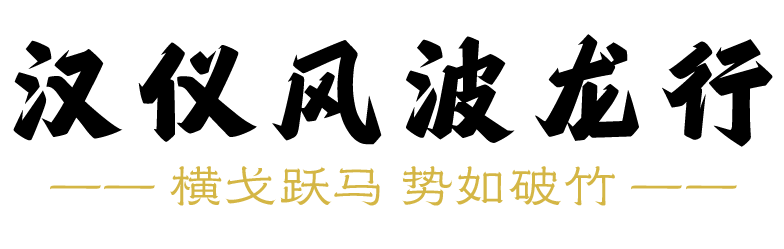
汉仪风波龙行字体介绍,看字体如何行走江湖,势如破竹!
粗壮 / 阳刚 / 动感 / 潇洒
标志 / 书籍 / 广告 / 杂志 / 游戏 / 动漫 / 影视 / 包装
汉仪风波龙行是一款将粗黑体与行楷字体有机结合的字体,由汉仪签约设计师梁风波创作。这款字体既保留了黑体粗壮有力的特征,由能展现出行楷字体的流畅自如的感觉,气势磅礴、潇洒风流。故该字体应用在各种标题、标语等场合,以展现出势如破竹的行动力、横戈跃马的英勇姿态、以及笙歌鼎沸的盛世气象。
汉仪风波龙行中宫收紧、左低右高、左收右放,有昂扬向上的态势。笔画棱角明显、起收转折有力,宛如行走江湖仗义凛然的侠客,在黑白之间横槊赋诗,充满阳刚之气。
为了体现出较快的书写速度,设计师在笔画的起收处都添加了大量的牵丝,以体现笔画之间的映带关系。同时设计师也创作了大量的连笔结构,使得字形变化更加丰富多样,充满书写感。
汉仪风波龙行笔画粗厚,使得该字体与一般的楷书字体比起来要更为醒目。布点简洁,点到为止,点与点之间的曲线有着微妙的向外拱起的弧度,使得笔画更加饱满有力。宛如山峦巨石,震天骇地,矗立不倒。
汉仪风波龙行的西文部分由汉仪字库的西文设计师刘嫣然设计。字母起收笔切角成一定角度倾斜,使字形看起来既充满古韵,又带有一丝动感。小写字母参照意大利体的造型设计,体现出较快的书写速度。较高的x字高于装饰衬角使得西文与中文匹配和谐一致,充满力量与动感。